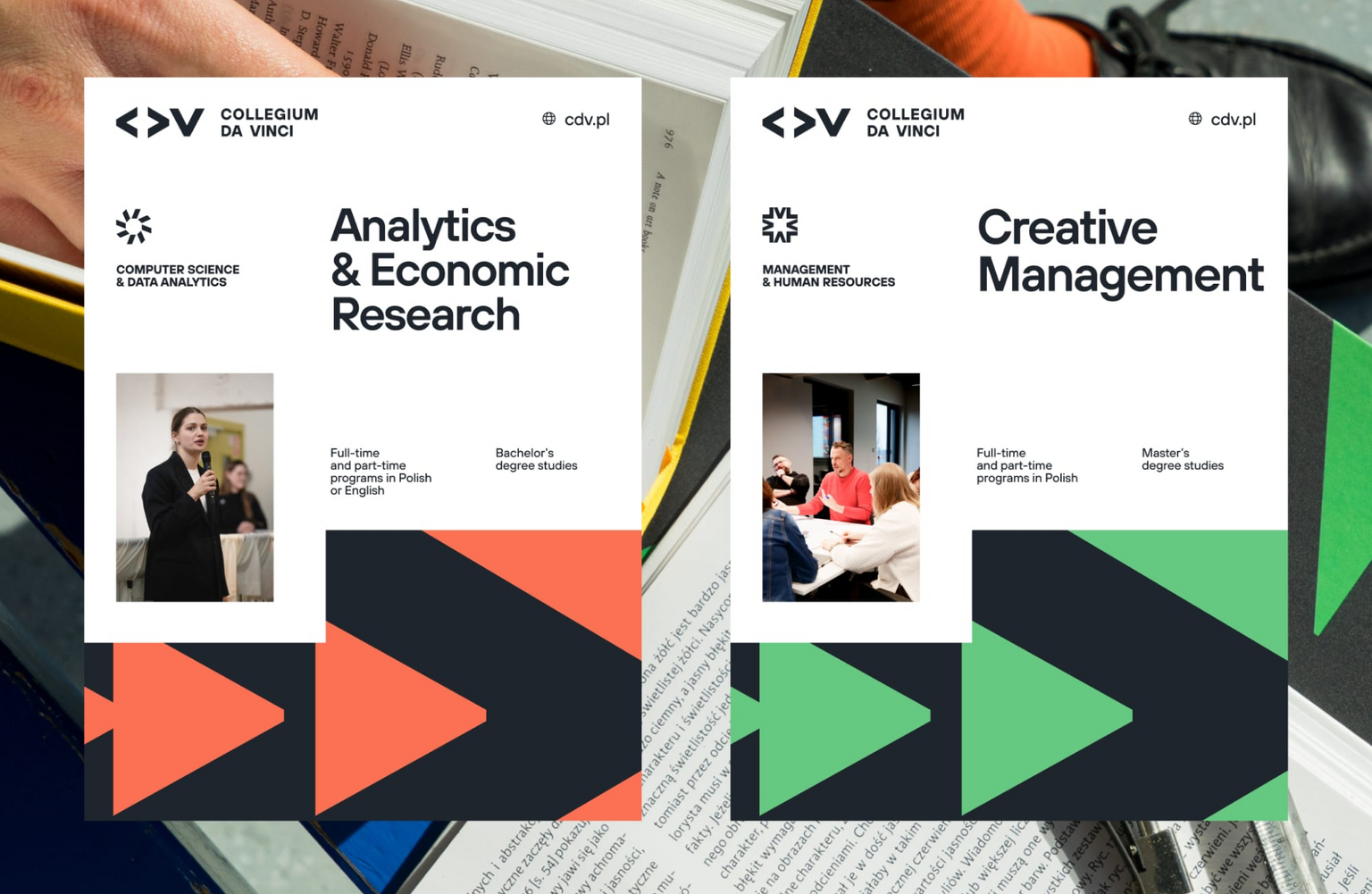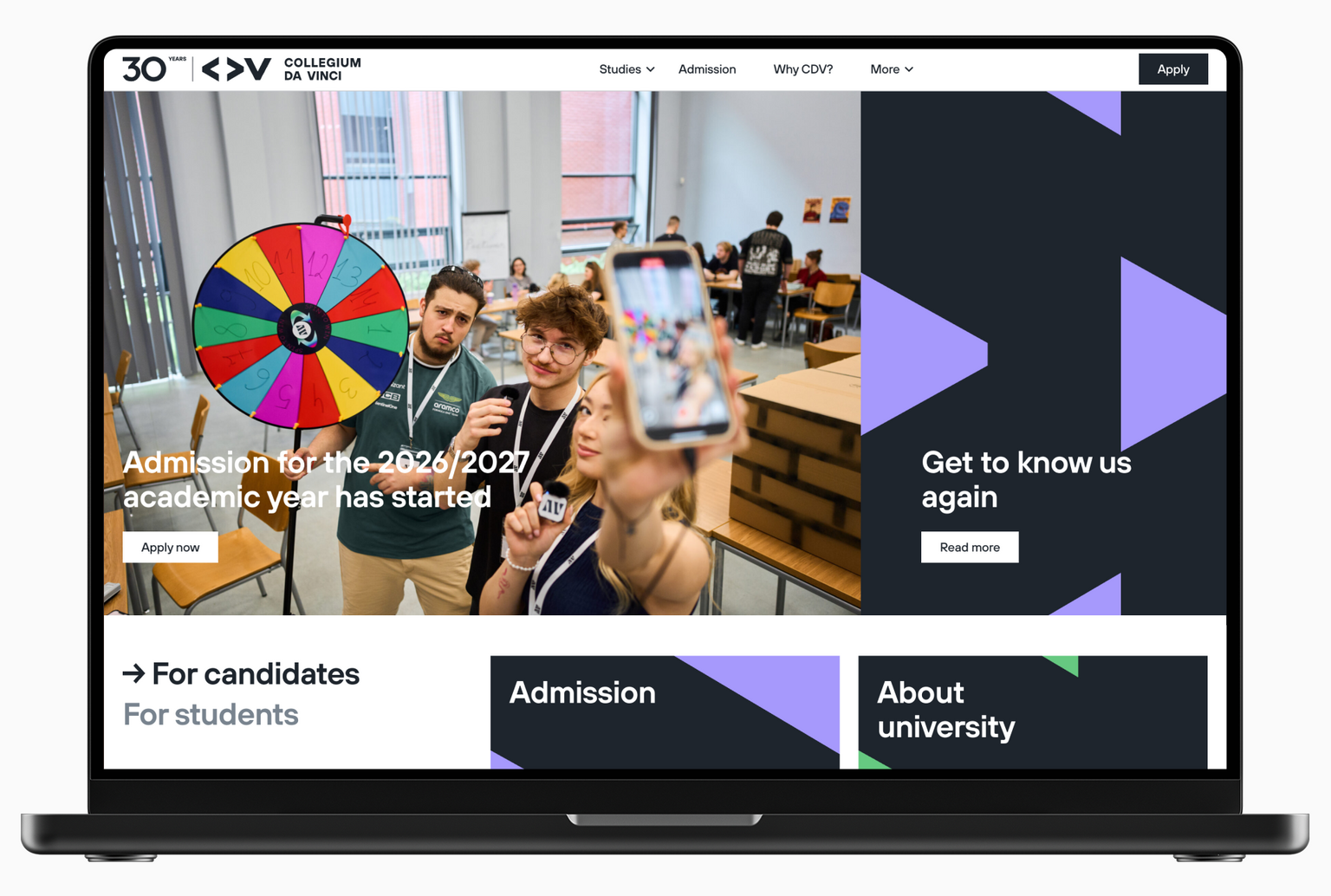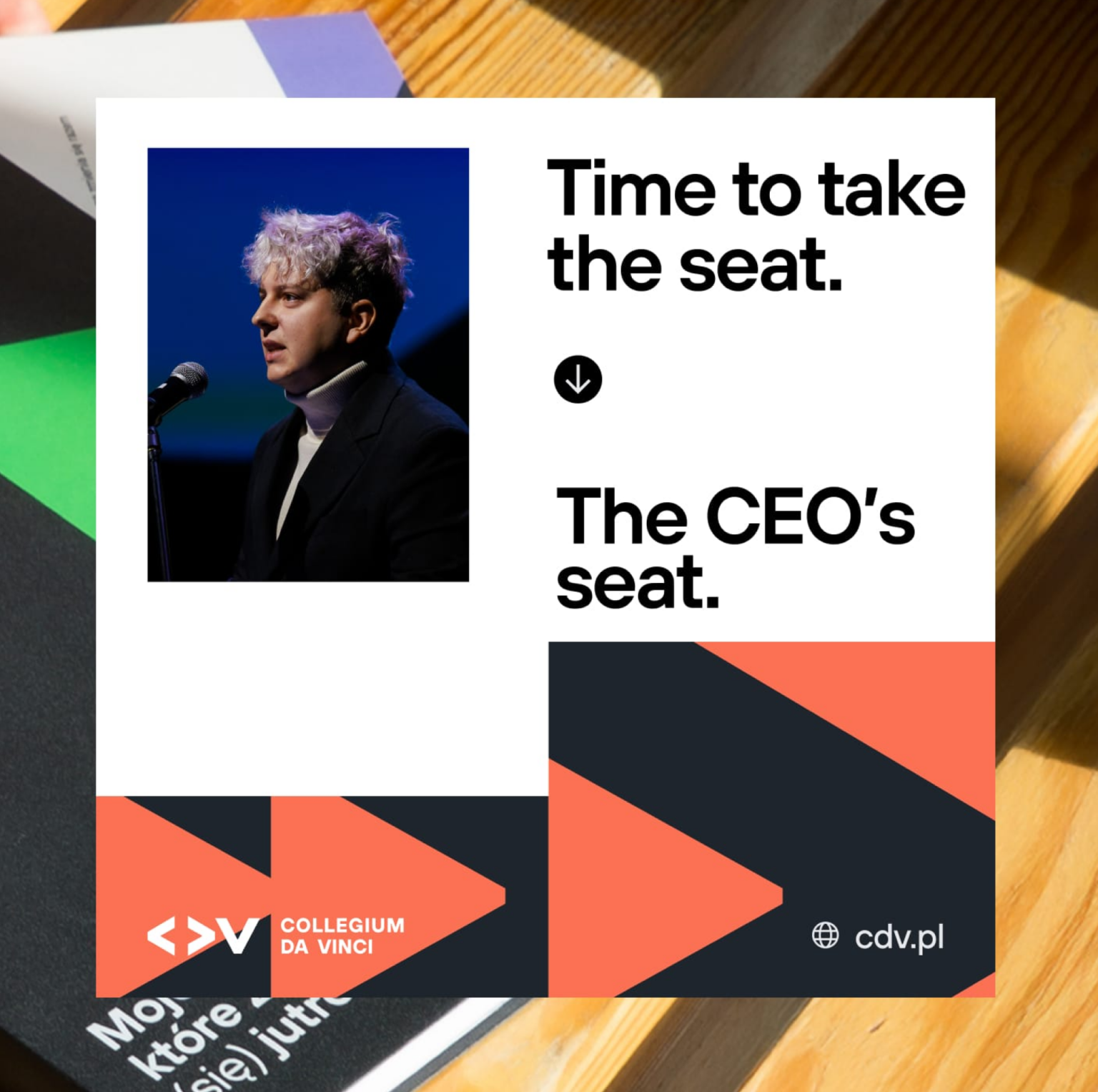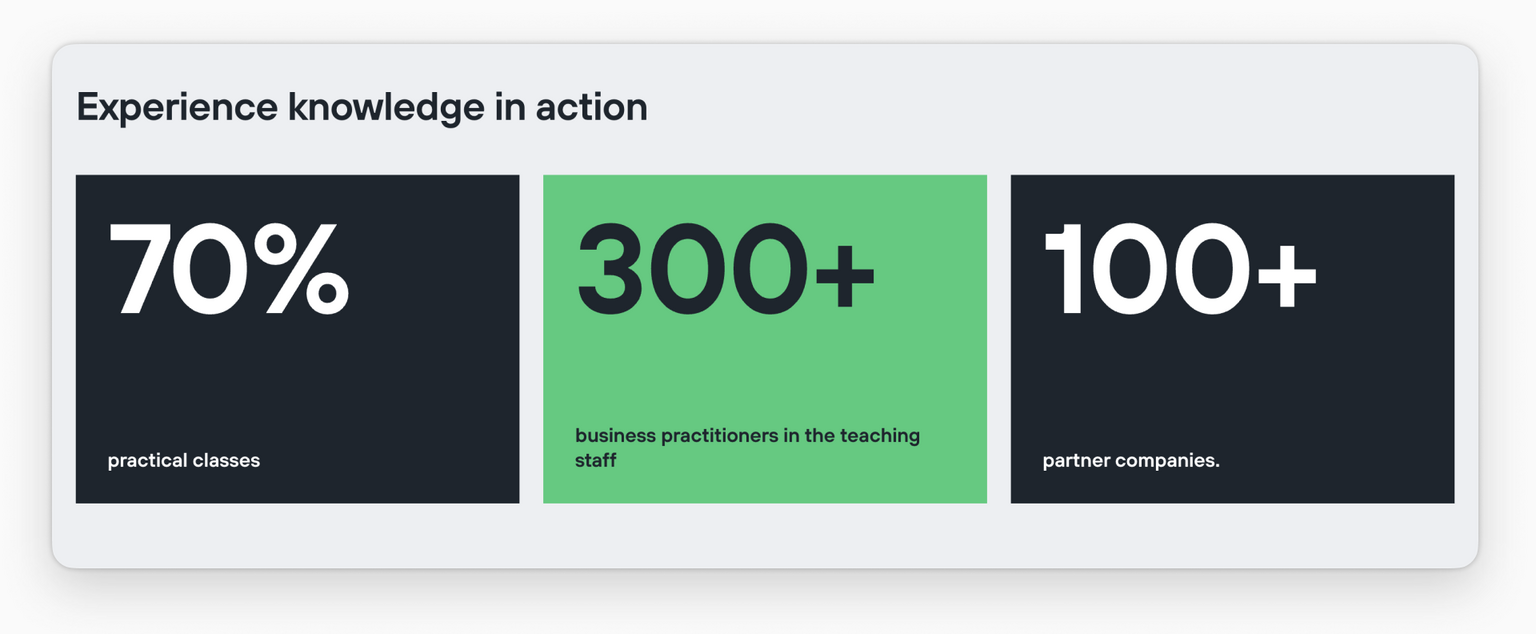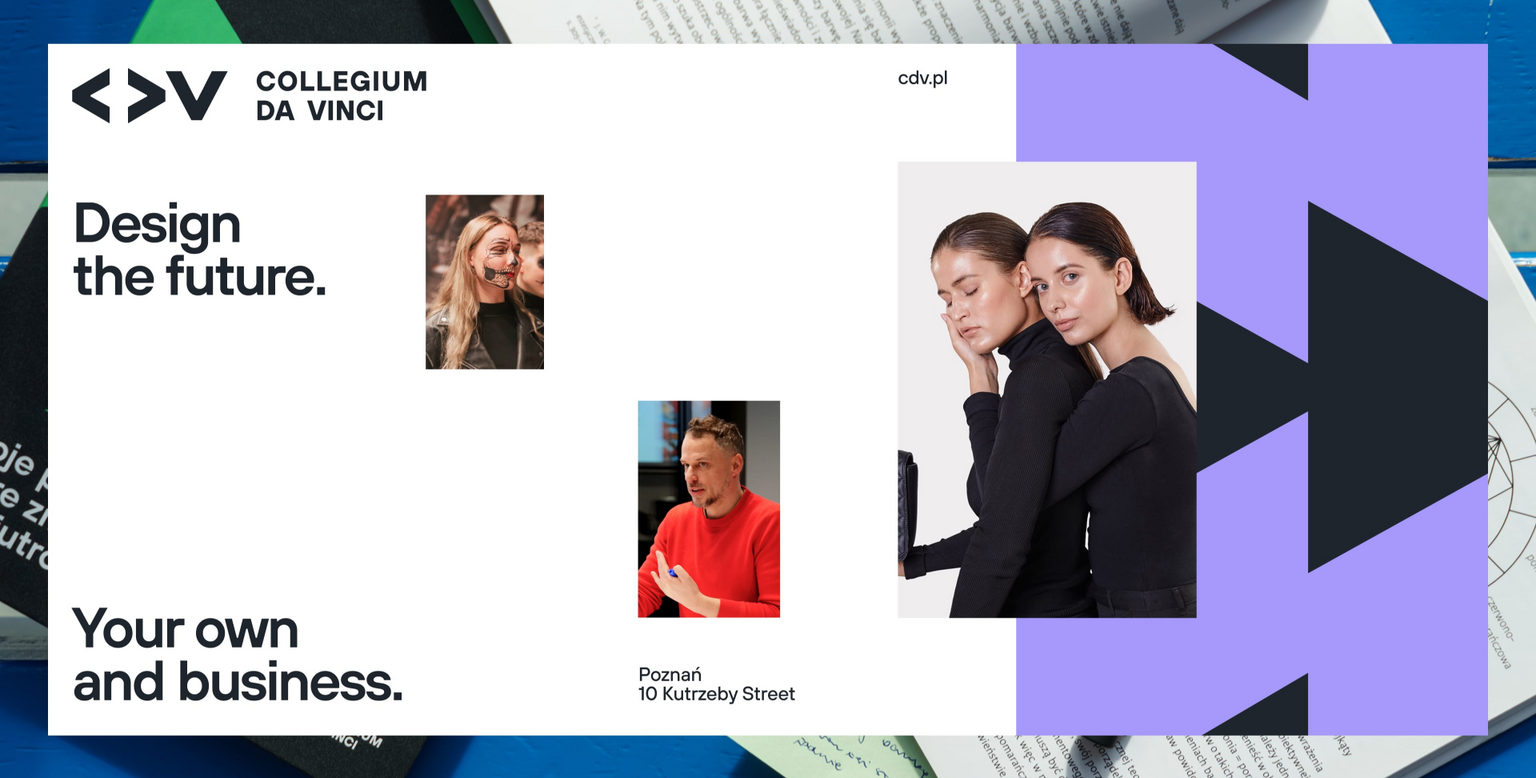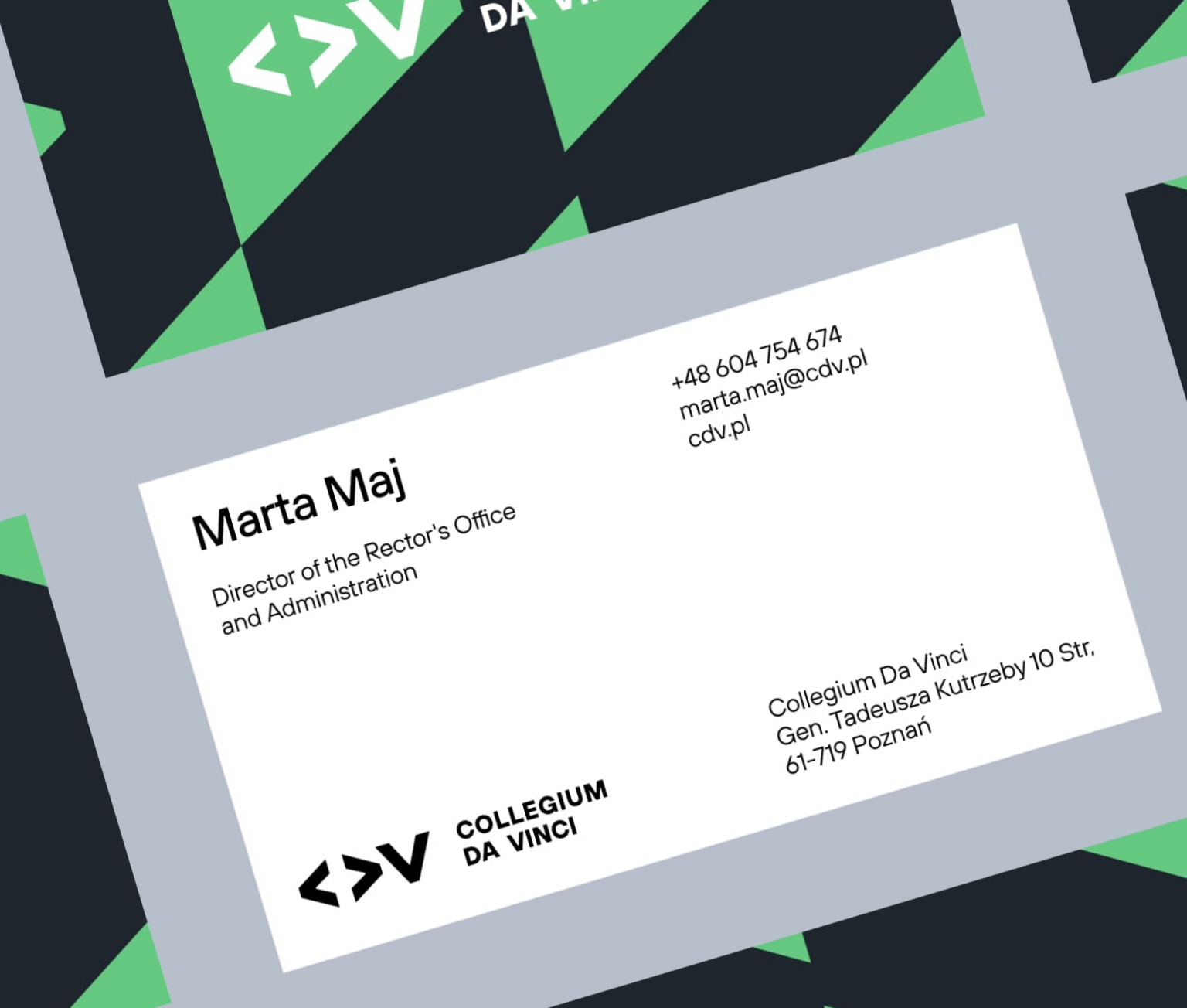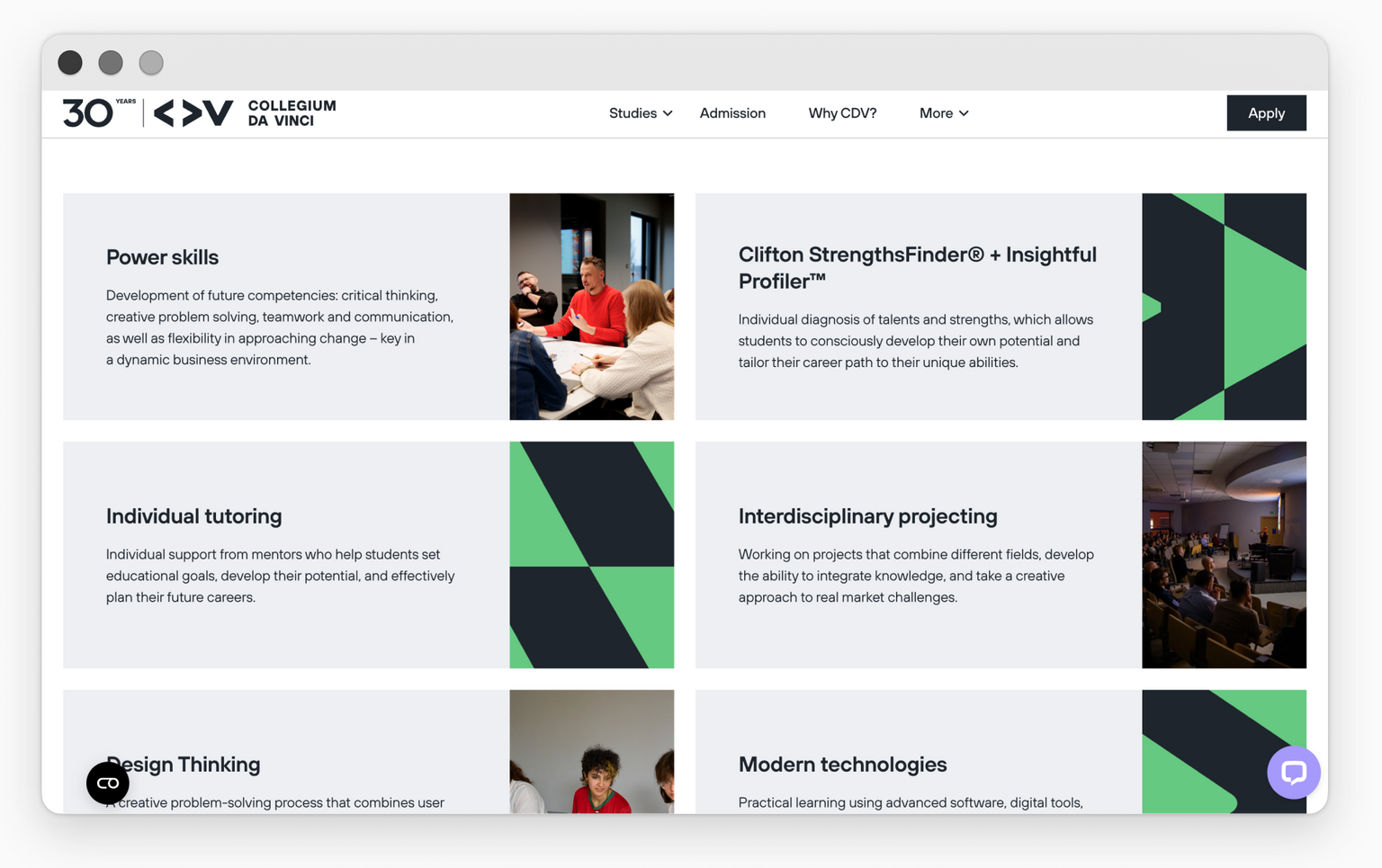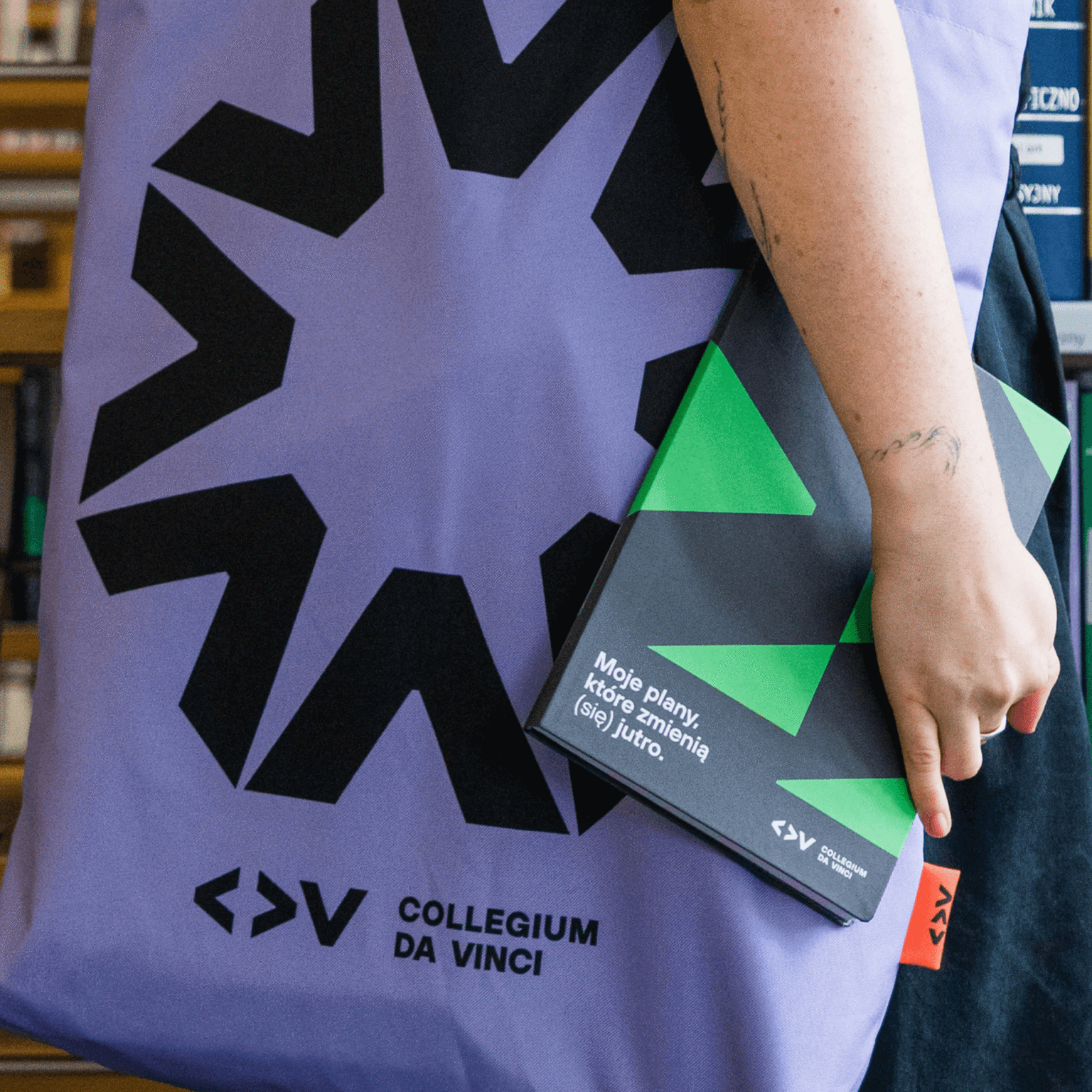
Скандинавский гротеск TT Hoves Pro используется в айдентике университета Collegium Da Vinci.
Collegium Da Vinci — частный польский университет, который делает акцент на практико-ориентированном обучении, сотрудничестве с бизнесом и подготовке студентов к современному рынку труда. Шрифт помогает сформировать современный и дружелюбный образ университета.